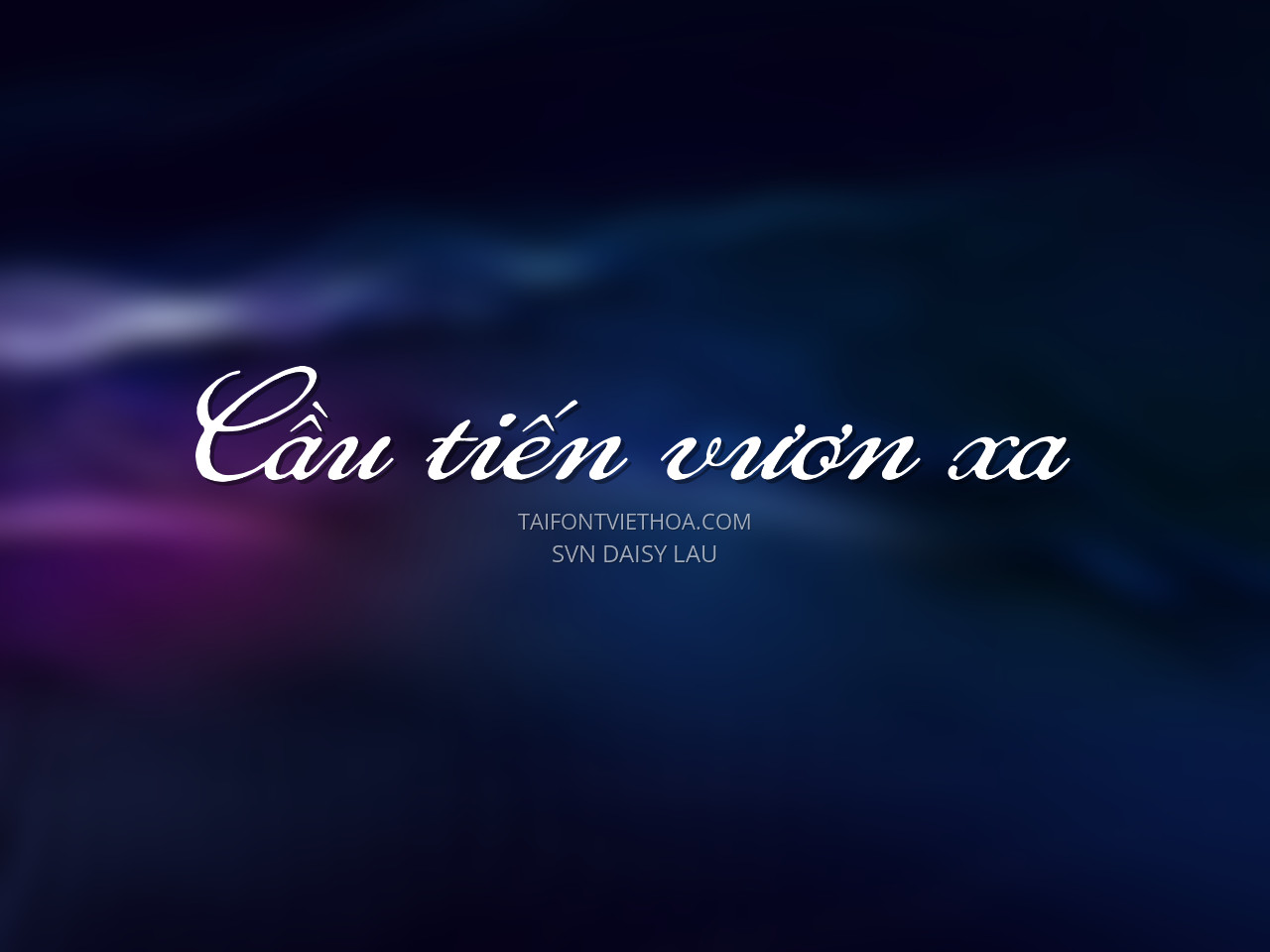
Font việt hóa SVN Daisy Lau
Tác giả Font: Ryoichi Tsunekawa
Giới thiệu về font SVN Daisy Lau – Kiểu chữ handwritten mềm mại, nữ tính và thanh lịch
SVN Daisy Lau là phiên bản Việt hóa của font Daisy Lau – một kiểu chữ handwritten mang phong cách mềm mại, nữ tính và rất thanh lịch. Font được thiết kế với những nét chữ uyển chuyển, nhẹ nhàng và duyên dáng, tạo cảm giác tinh tế và gần gũi, rất phù hợp cho các dự án thiết kế thiệp cưới, thiệp mời, bao bì mỹ phẩm và các sản phẩm sáng tạo cá nhân.
Phiên bản Việt hóa của SVN Daisy Lau đã được Taifontviethoa.comchăm chút kỹ lưỡng, hỗ trợ đầy đủ dấu tiếng Việt cùng hơn 60 ngôn ngữ khác. Font giữ nguyên nét mềm mại, bay bổng và tự nhiên của bản gốc, giúp các nhà thiết kế dễ dàng áp dụng trong nhiều dự án sáng tạo với phong cách nhẹ nhàng, thanh lịch và duyên dáng.
Thiết kế viết tay uyển chuyển – Lý tưởng cho thiệp cưới và thương hiệu mỹ phẩm
SVN Daisy Lau sở hữu các nét chữ mềm mại, liền mạch với độ nghiêng nhẹ nhàng và các ligature tinh tế, tạo nên sự hài hòa và bay bổng trong tổng thể thiết kế. Font mang lại cảm giác nữ tính, duyên dáng và rất phù hợp cho tiêu đề, logo, bao bì hoặc các phần thiết kế cần điểm nhấn mềm mại và thanh lịch.
Ứng dụng lý tưởng: thiệp cưới, thiệp mời, logo thương hiệu mỹ phẩm, bao bì sản phẩm cao cấp, bìa sách nghệ thuật, poster sự kiện và các dự án sáng tạo cần phong cách nhẹ nhàng, duyên dáng. Ngành nghề phù hợp: cưới hỏi, mỹ phẩm, thời trang, nghệ thuật, truyền thông sáng tạo và các thương hiệu định vị theo phong cách nữ tính, thanh lịch.